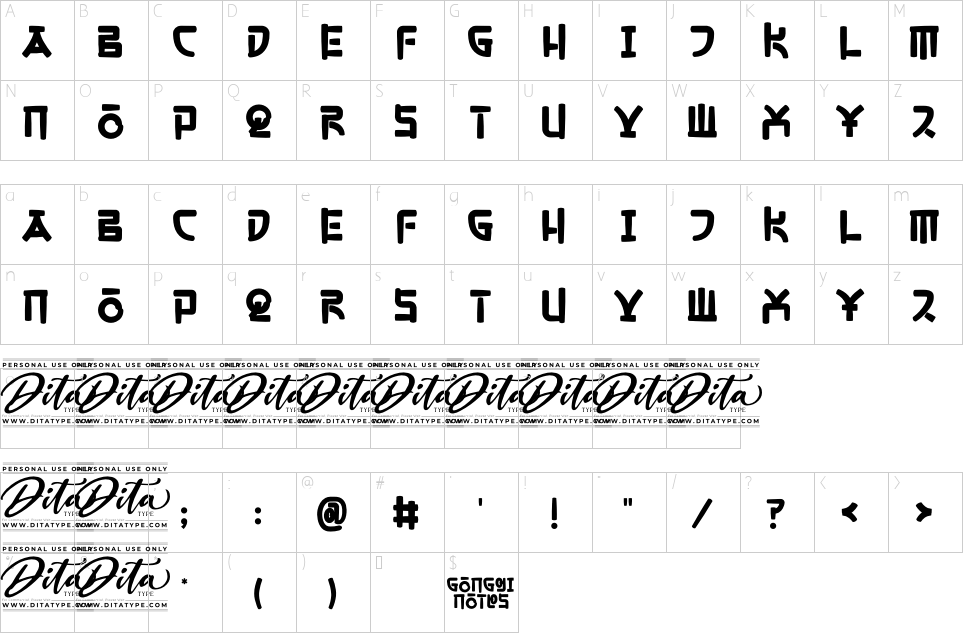
Descubra Gonggi Notes Font – uma elegante opção para escrita diária. Desenvolvida pela Dita Type, essa fonte foi projetada para quem busca uma mistura suave entre modernidade e estilo clássico. Com um design cuidadosamente elaborado, Gonggi Notes é perfeita para uso em websites, impressões ou qualquer projeto de escrita. Possui 1001 Free Fonts categoria e com seu download fácil, você pode incorporar esta fonte incrível aos seus trabalhos, proporcionando uma textura única que tornará suas criações únicas ainda mais chamativas. É claro que essa font se destaca por sua simplicidade e facilidade de uso, tornando-a um ótimo complemento para qualquer projeto de design gráfico. Em Gonggi Notes Font você encontrará a perfeição na intersecção do modernismo e da elegância clássica.